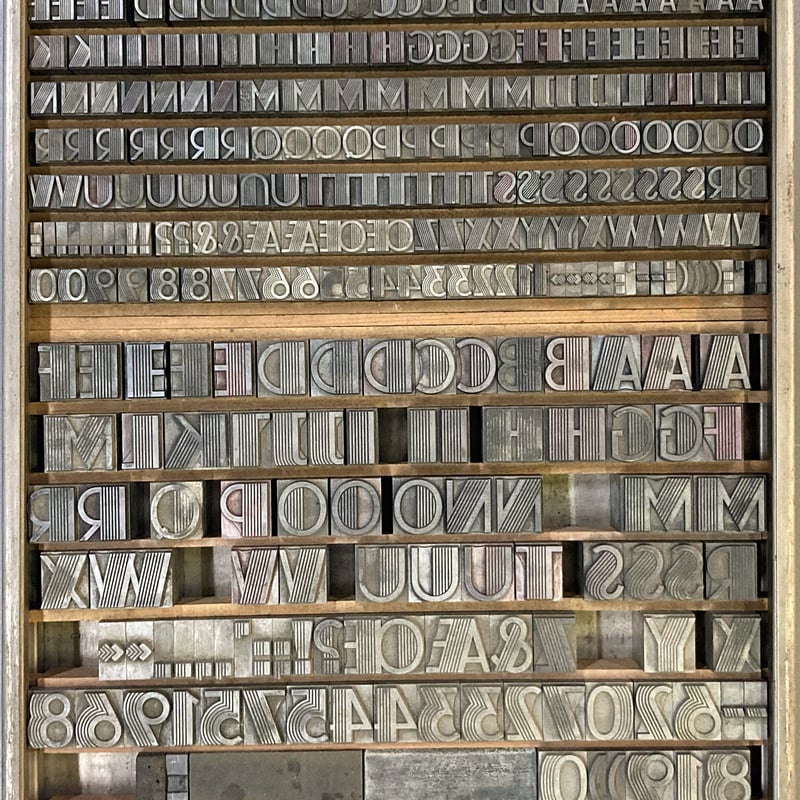
Fatima
Druckmuster mit Text «Fatima, 28pt»
Klassifizierung
Display, Shadow
Design
Karl Hermann Schäfer
Jahr
1933
Schriftgiesserei
Schriftguss
Die Schrift wurde auch unter den Namen Atlas (Fonderie Typographique Française), Gopło (Idźkowski) sowie Reclame (Fonderia Tipografica Cooperativa) vertrieben.
Zeichen
ABCDEFGHIJKLMNOPQRSTUVWXYZ0123456789!&(),-.:;?«»ÆŒ’
Grossbuchstaben
A-Z
Kleinbuchstaben
nicht vorhanden
Zahlen
0-9
Sonderzeichen
! & ( ) , - . : ; ? « » Æ Œ ’